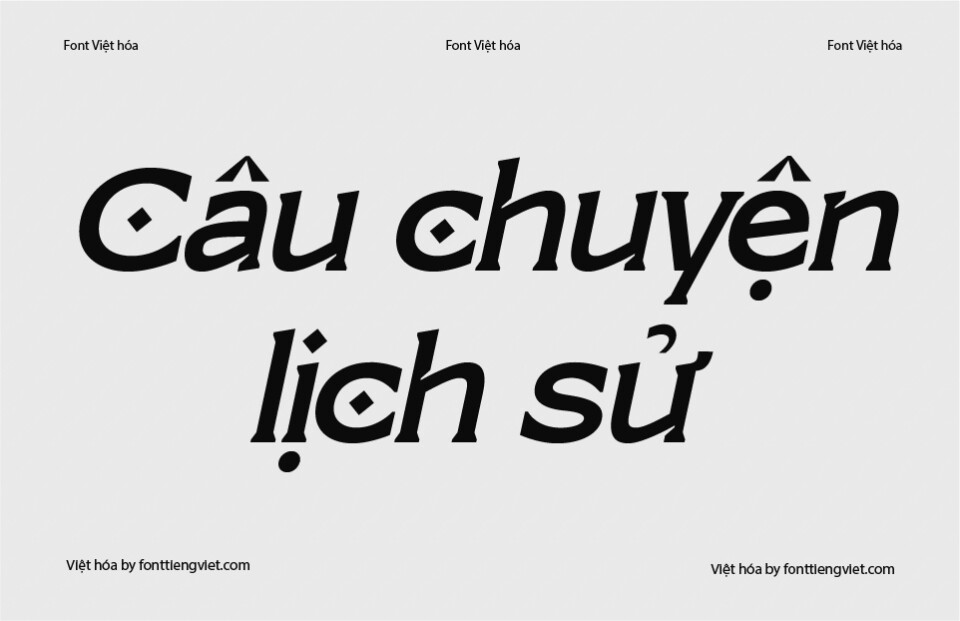
Font việt hóa Qatteo Italic đẹp dành cho thiết kế
Qatteo Italic là một kiểu chữ mang phong cách script nghiêng hiện đại, được thiết kế với mục tiêu tạo nên sự thanh thoát, nghệ thuật và duyên dáng trong từng con chữ. Với những đường nét uốn lượn mềm mại, kết hợp cùng độ nghiêng đặc trưng, Qatteo Italic mang đến cảm giác nhẹ nhàng, bay bổng, rất thích hợp cho các thiết kế mang tính cá nhân hóa, sáng tạo hoặc lãng mạn.
Đặc điểm nổi bật của font Qatteo Italic
• Kiểu chữ nghiêng nghệ thuật: Qatteo sử dụng kiểu chữ nghiêng (italic) với các nét bút thanh mảnh, tạo cảm giác chuyển động mềm mại và tinh tế.
• Nét viết tay kết hợp hiện đại: Font mô phỏng phong cách chữ viết tay nhưng được tinh chỉnh kỹ lưỡng, giúp vừa giữ được cảm xúc thủ công, vừa đảm bảo tính thẩm mỹ trong thiết kế số.
• Độ bay bổng cao: Các ký tự có độ cao và cong lớn, tạo ra hiệu ứng như chữ đang “lướt nhẹ” rất thu hút trong các tiêu đề hoặc tên thương hiệu.
• Việt hóa chỉn chu: Các dấu và ký tự tiếng Việt được tinh chỉnh cẩn thận, không làm phá vỡ bố cục gốc của font, từ đó giúp bạn sử dụng thoải mái trong thiết kế tiếng Việt.
Ứng dụng của font Qatteo Italic
Font Qatteo Italic rất phù hợp cho các thiết kế yêu cầu sự duyên dáng, mềm mại, mang yếu tố nghệ thuật và cá tính riêng:
• Thiệp cưới, thư mời, lời chúc: Với phong cách lãng mạn và uyển chuyển, font Qatteo Italic là lựa chọn hoàn hảo cho các thiết kế mang tính cảm xúc.
• Logo thương hiệu cá nhân, spa, mỹ phẩm: Font giúp thể hiện sự chuyên nghiệp nhưng vẫn gần gũi, đặc biệt hợp với các thương hiệu mang hơi hướng nữ tính và sáng tạo.
• Typography nghệ thuật & trích dẫn: Các thiết kế poster trích dẫn, typography truyền cảm hứng sẽ trở nên sinh động và cá nhân hóa hơn với Qatteo Italic.
• Bìa sách, blog cá nhân, portfolio: Giúp tạo điểm nhấn nhẹ nhàng nhưng đầy thu hút, nâng tầm phong cách cá nhân cho các sản phẩm sáng tạo.
Qatteo Italic không chỉ là một font chữ đẹp, mà còn là một ngôn ngữ thị giác thể hiện sự duyên dáng, tinh tế và đầy tính nghệ thuật. Nếu bạn đang tìm một kiểu chữ vừa mềm mại vừa sang trọng để tạo dấu ấn cho thiết kế của mình, Qatteo Italic là lựa chọn đáng cân nhắc.